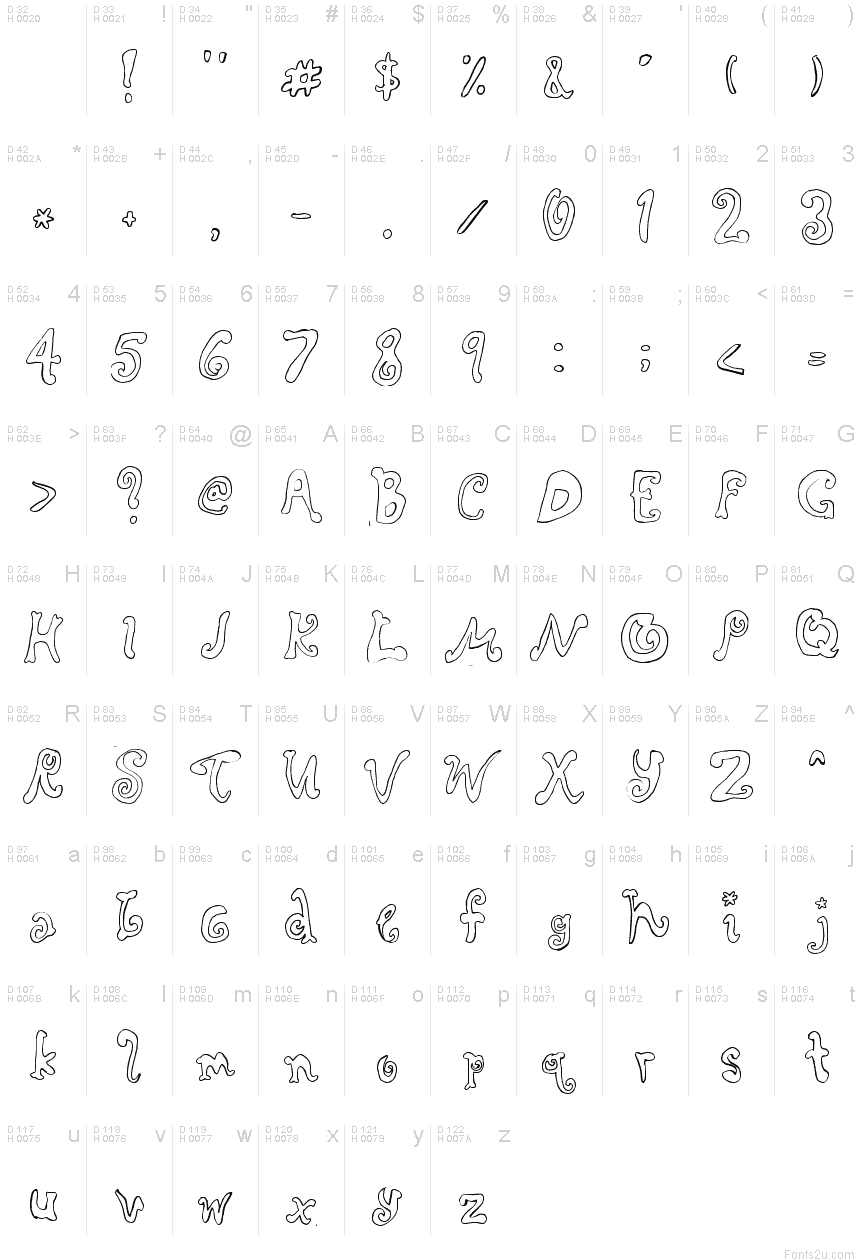
Rascal to darmowy, konturowy krój pisma od Tommy’ego Cary’ego – kreskówkowy alfabet pełen luźnych zawijasów i odręcznego charakteru. Litery są zabawne i nieco niepokorne, o pękatych kształtach, miękkich, nierównych liniach i powtarzających się skrętach, które nadają całości zadziorną, bajkową energię.
Dzięki temu ten darmowy font świetnie sprawdzi się na okładkach książek dla dzieci, w komiksowych tytułach, na szyldach sklepów, zaproszeniach i nietuzinkowych plakatach, gdzie kręty rytm znaków mówi sam za siebie. Nadaje się również do krótkich logotypów, monogramów i inicjałów – duże pętle sprawiają, że nawet kilka liter wygląda niezwykle efektownie.